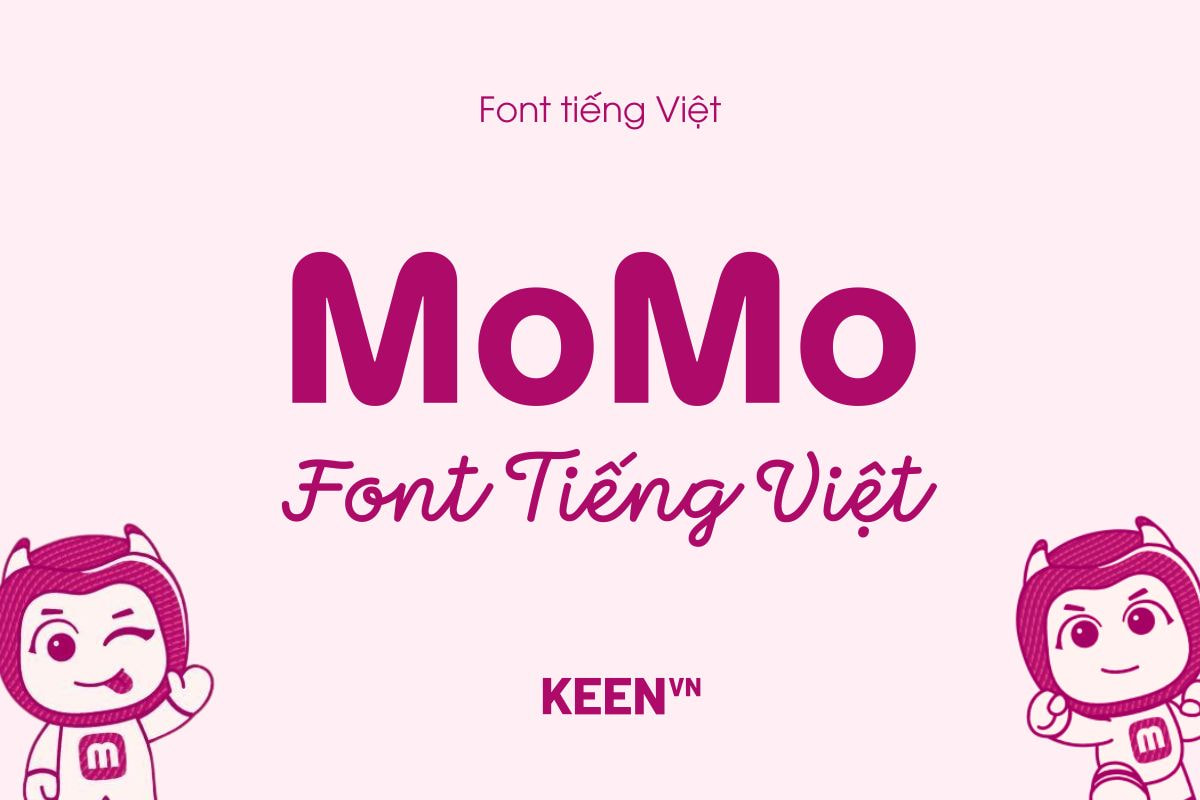
Font tiếng Việt Momo là một bộ phông chữ mang đậm dấu ấn thương hiệu, được xây dựng với sự chăm chút tỉ mỉ để truyền tải cảm giác tin cậy, gần gũi và tính kết nối xuyên suốt trong mọi thiết kế. Bộ font bao gồm ba kiểu chữ: MoMo Trust Display, Trust Sans và MoMo Signature, mỗi kiểu mang một cá tính riêng nhưng vẫn hòa quyện hài hòa để tạo nên bản sắc thị giác nhất quán. MoMo Trust Display và Trust Sans được phát triển dựa trên chính biểu tượng đặc trưng của MoMo, với những đường bo tròn mềm mại và thân thiện, phản ánh tinh thần công nghệ hiện đại nhưng vẫn đáng yêu, dễ tiếp cận. Chúng đặc biệt phù hợp cho các dự án đòi hỏi sự rõ ràng, tính nhận diện cao như giao diện ứng dụng, banner quảng cáo, tiêu đề hay nội dung truyền thông.
Trong khi đó, MoMo Signature đem đến một nét chấm phá nghệ thuật thú vị với cảm hứng từ chữ ký tay tự nhiên. Kiểu chữ này mang lại cảm giác chân thật và cá nhân hóa, giúp củng cố thông điệp về sự tin tưởng – yếu tố luôn xuất hiện trong hành trình kết nối người dùng của thương hiệu. Khi kết hợp cả ba kiểu chữ, bộ font Momo tạo ra một trải nghiệm thị giác trọn vẹn, vừa tinh tế, vừa đáng nhớ.